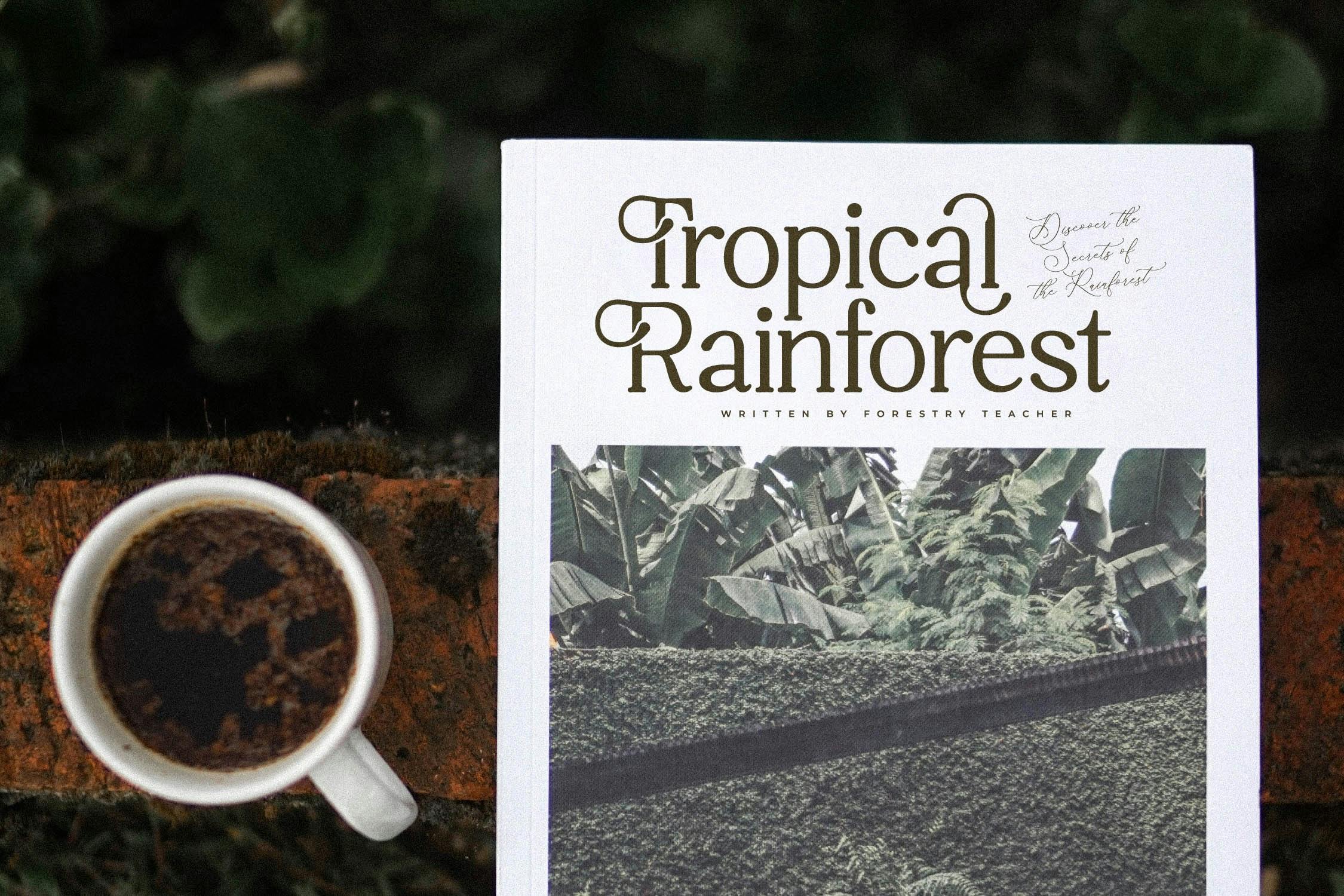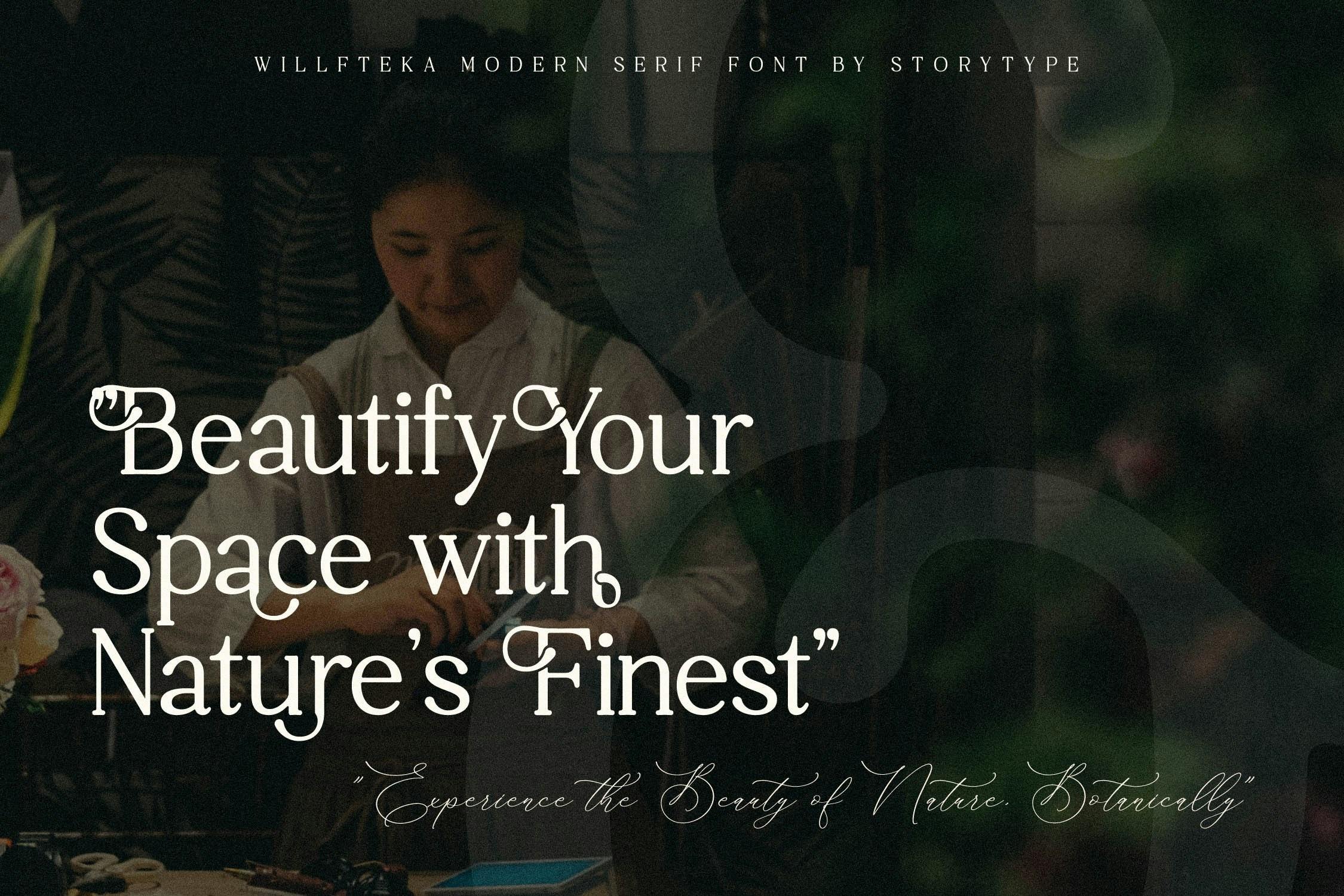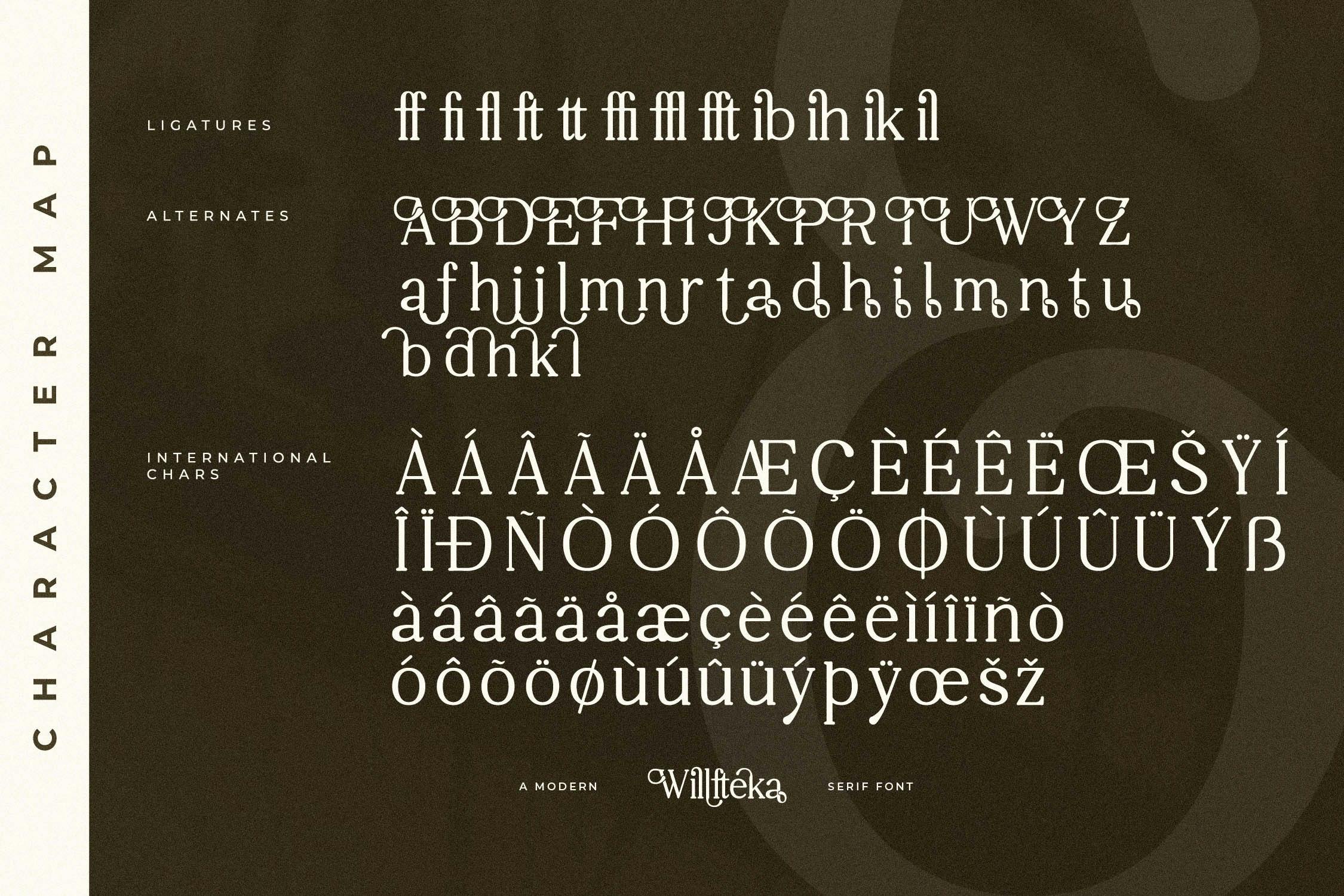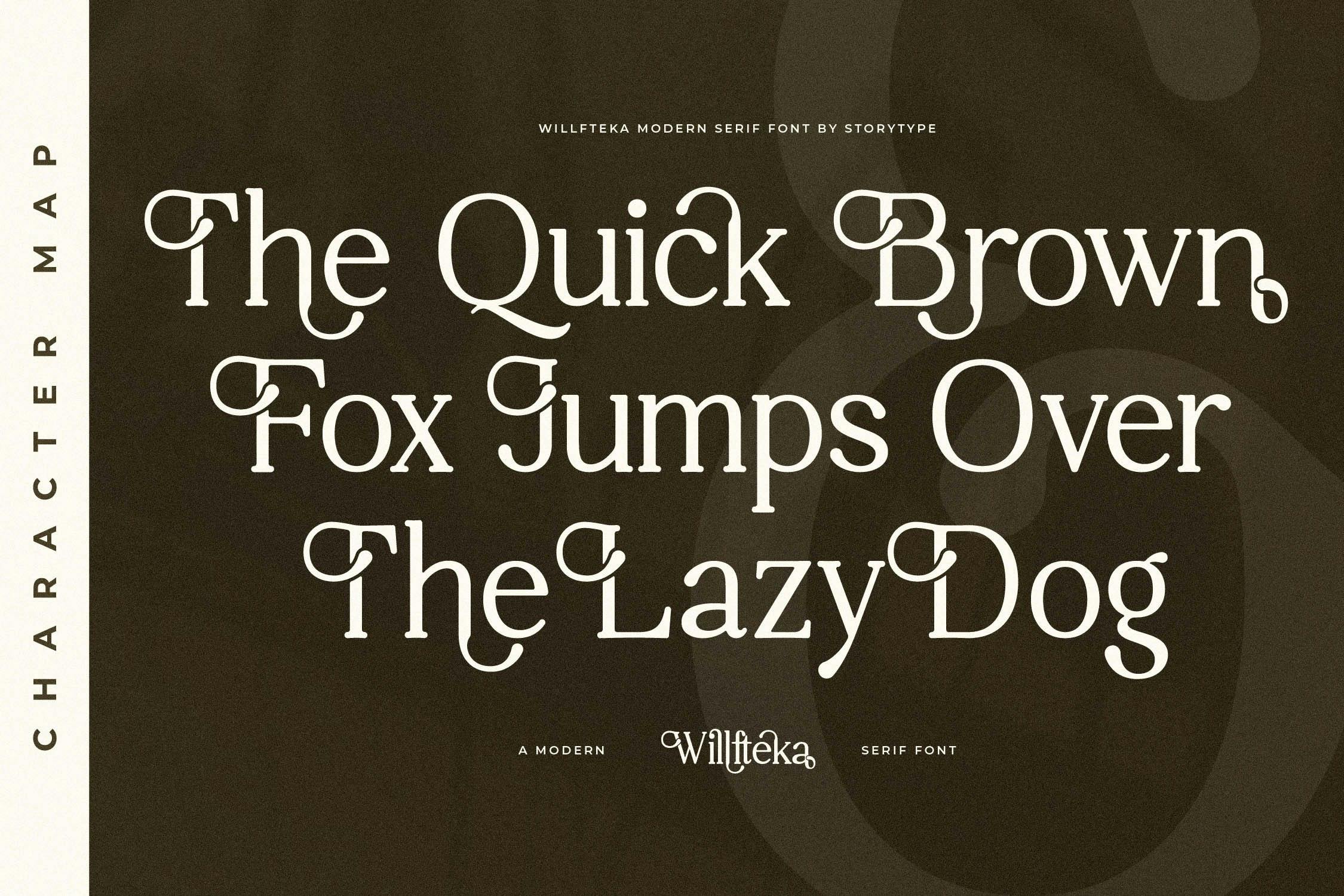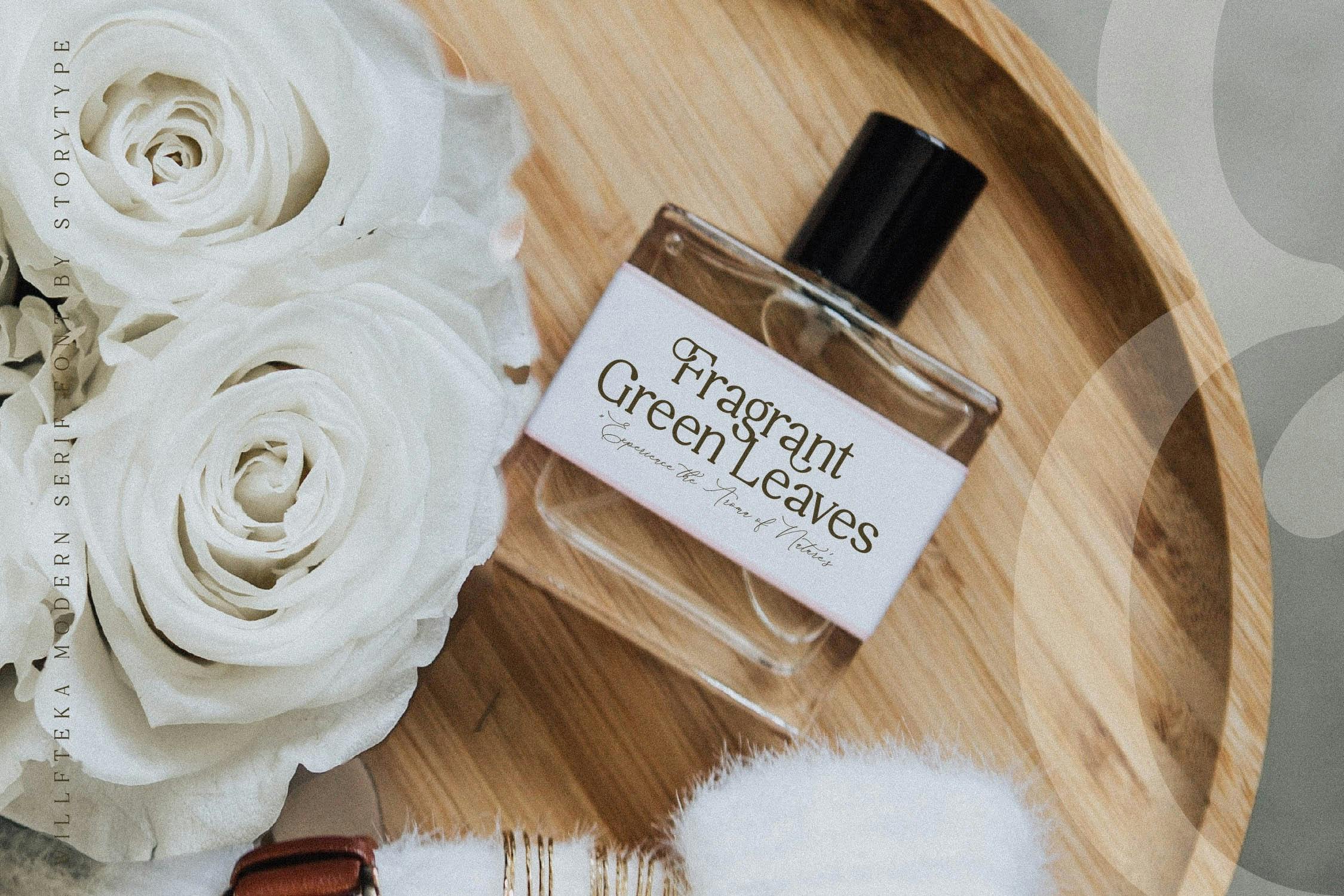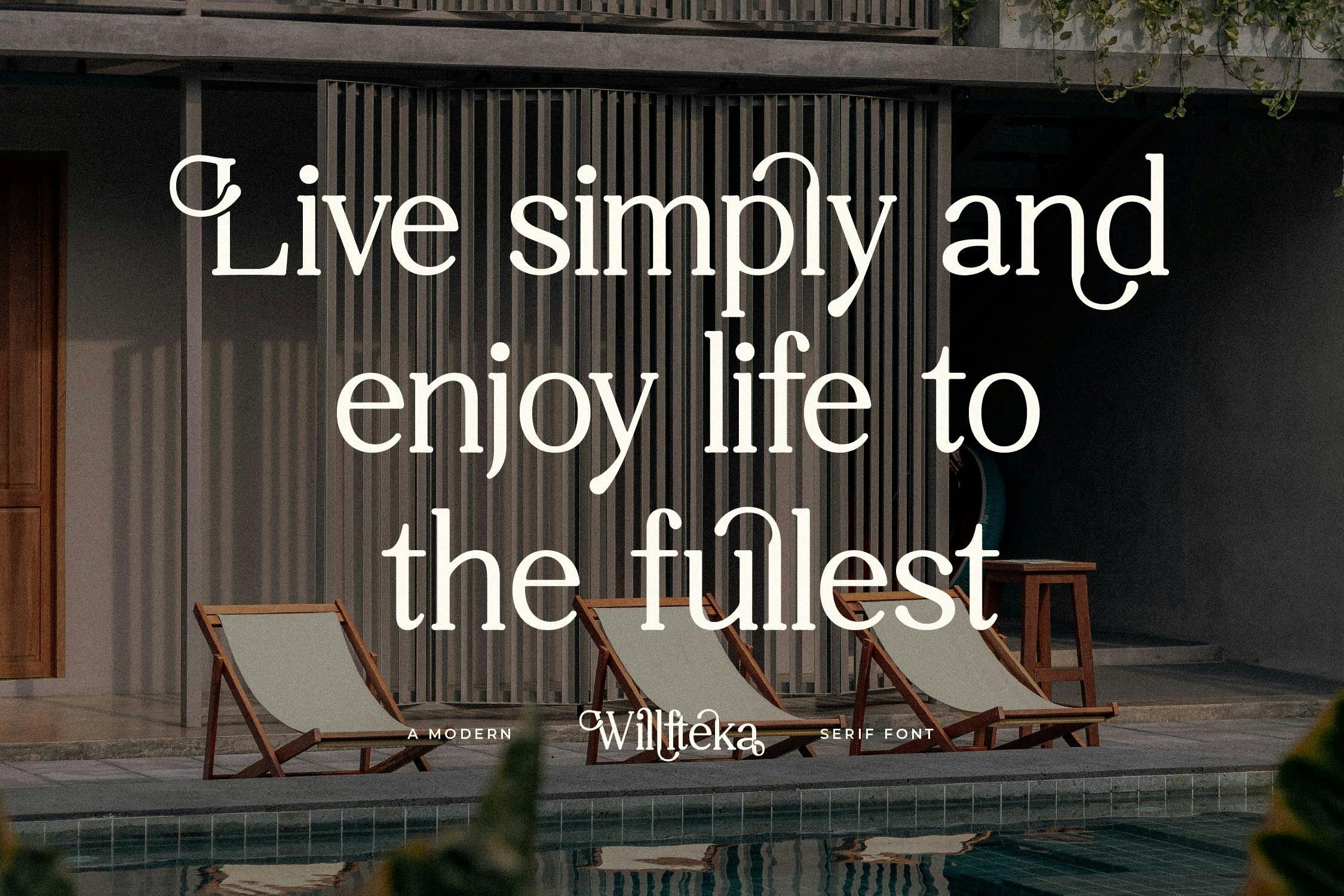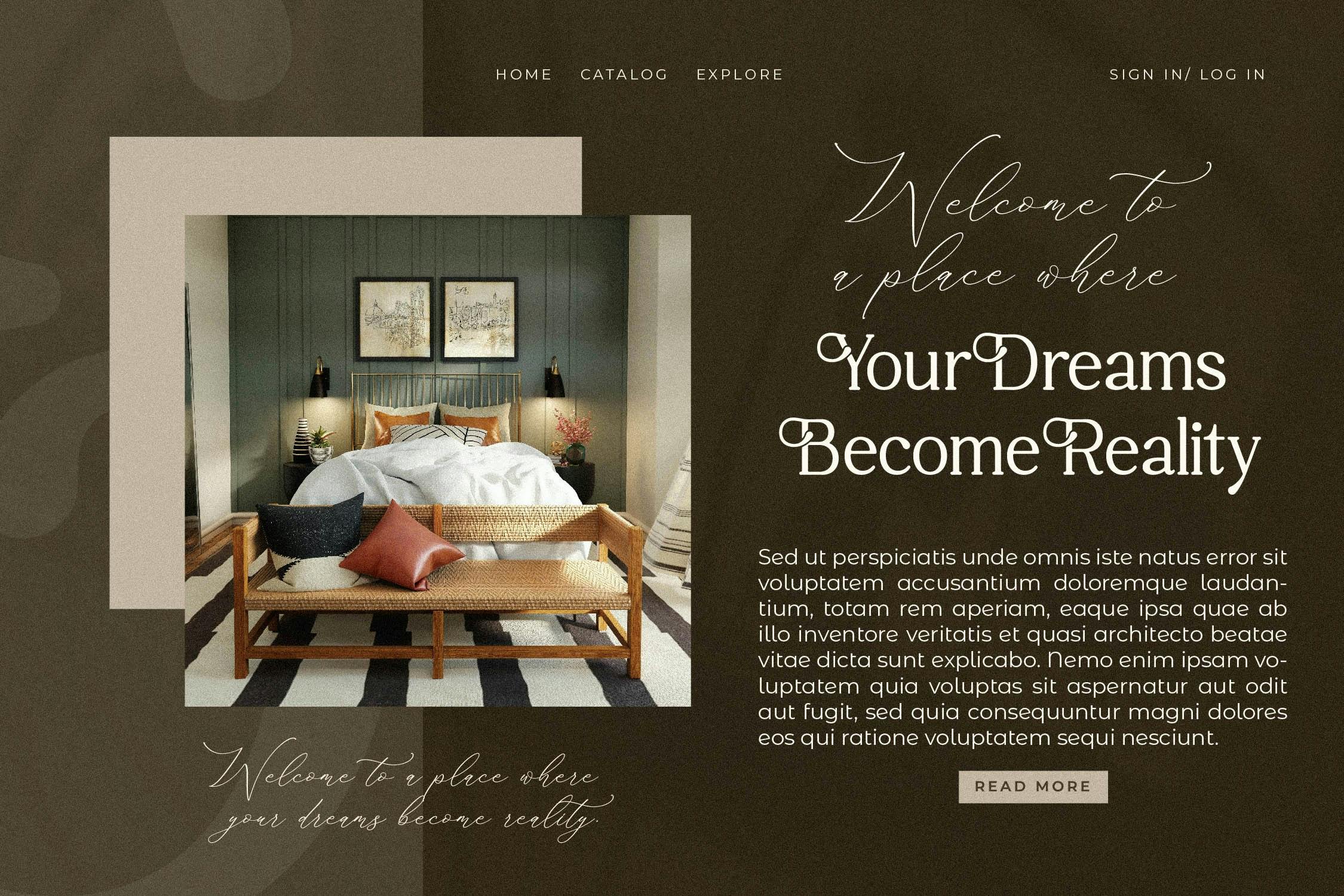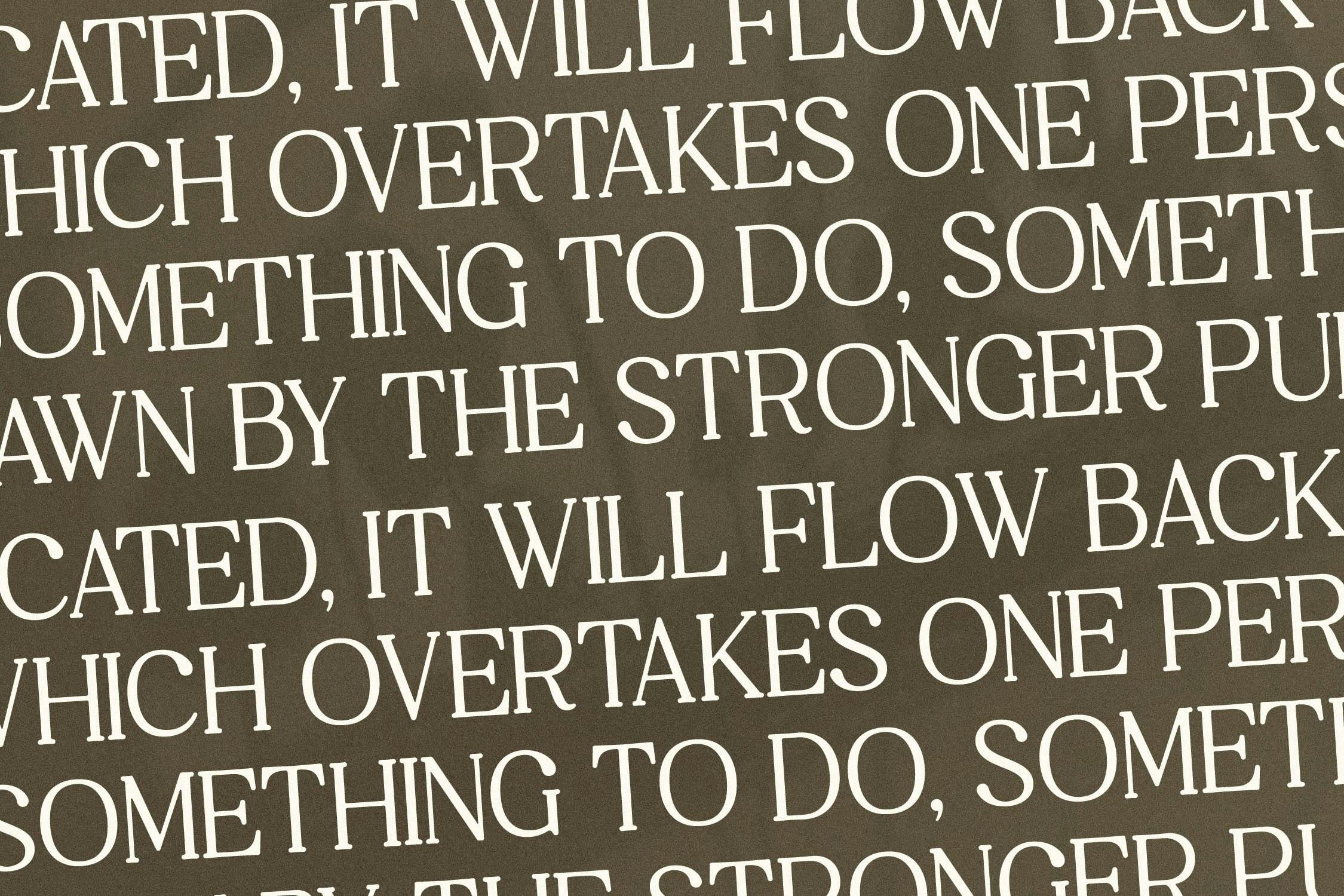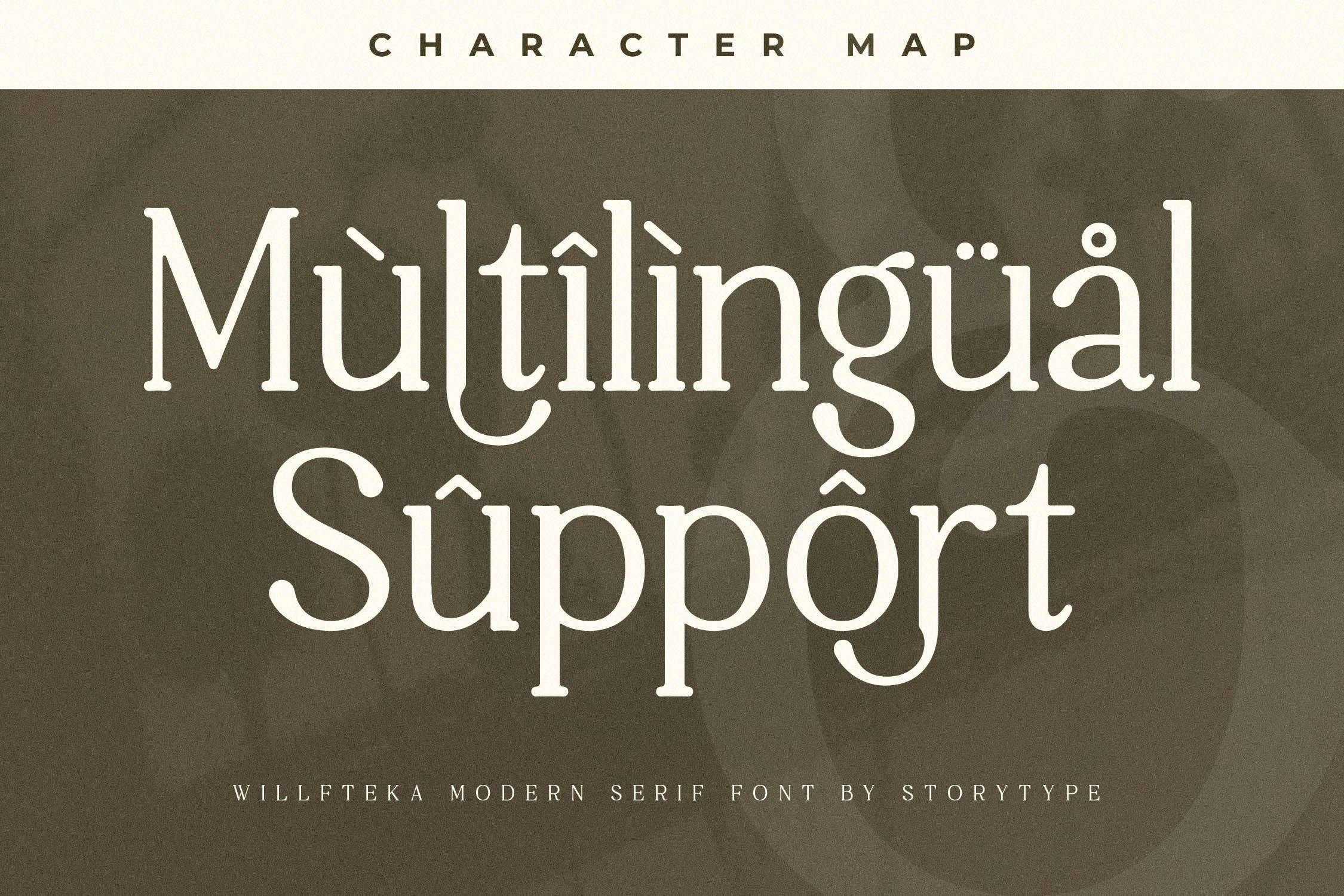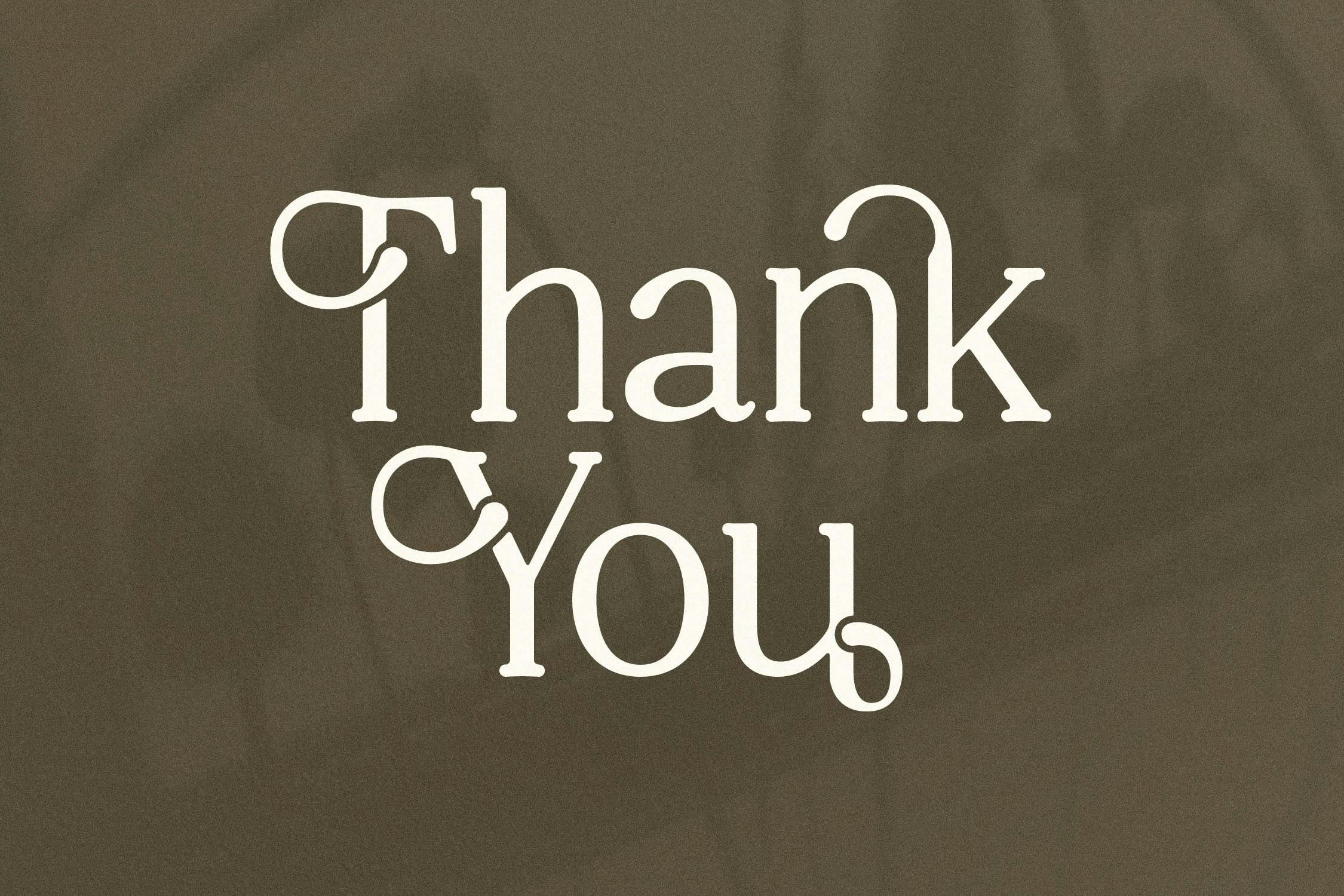
Willfteka A Modern Serif Font
فونت Willfteka انتخابی عالی برای پروژه‌های طراحی شماست.
سلام خانم‌ها و آقایان، این یکی از فونت‌های ماست که برای تکمیل محصولات خلاقانه دیجیتال و چاپی شما مناسب است. این فونت برای پوسترها، پست‌های رسانه‌های اجتماعی، برندینگ، پروژه‌های شخصی و غیره ایده‌آل است.